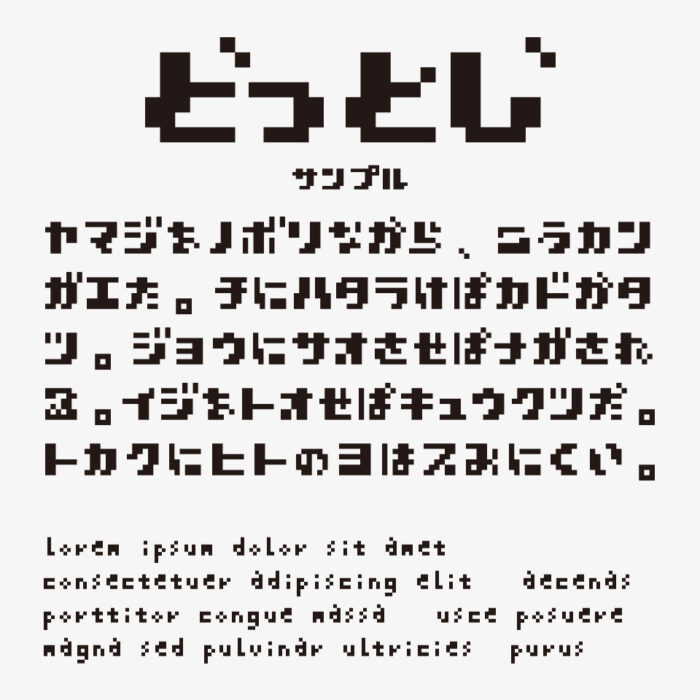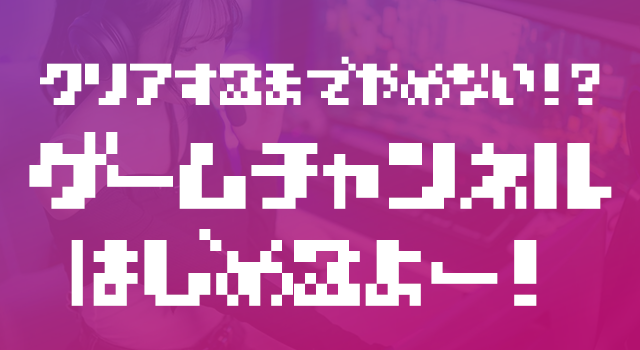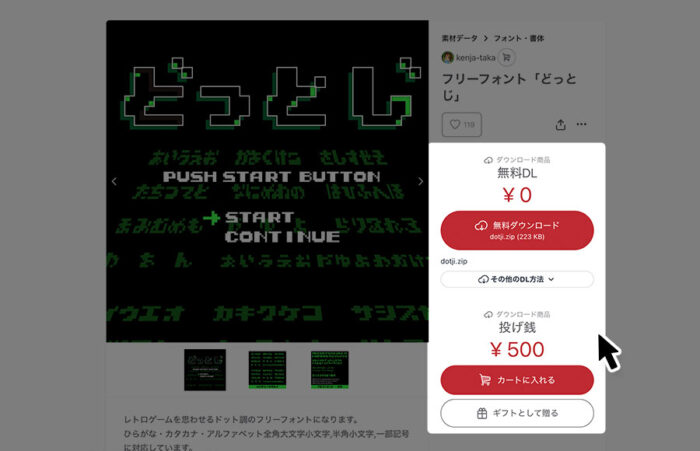
どっとじ
どっとじドットフォントは、極太ピクセルで構成されたようなドットフォントです。
レトロゲームやデジタルカルチャーを感じさせる無骨さが印象的で、だけど、どこか愛嬌があり、クセになるドットのデザインのフォントです。
遊び心がありながらも極太なので視認性が高く、アイキャッチとしての存在感も抜群です。ゲームロゴ、動画の字幕、サムネイルのビジュアルなどで使用すれば、デジタル感をぐっと引き立ててくれるフォントです。